CALLIGRA.Design免費藝術毛筆字素材下載網站,網頁蒐集了中國風、日本風的書法字體,有個性的美食文字、英文、日語、中文格言。不過並非是安裝字體,而是將現有的藝術文字素材下載成PNG(去背檔)、JPG、SVG向量圖檔在進行美編後製,可自訂文字顏色、大小。允許用於WEB網頁設計、海報雜誌等用途。
日本書法藝術字體素材
藝術書法文字 素材下載
前往CALLIGRA 毛筆字素材下載網站,依照類別搜尋所需要的文字。(如果日本頁面看不懂,可以直接將網頁翻譯成中文,會更方便使用唷)
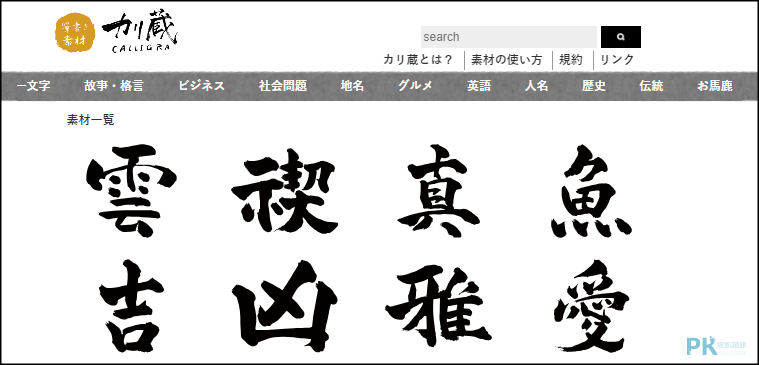
各式各樣的毛筆藝術文字素材,可自訂文字顏色、陰影、直書橫書排版,確認後選擇JPG,PNG,SVG格式下載。